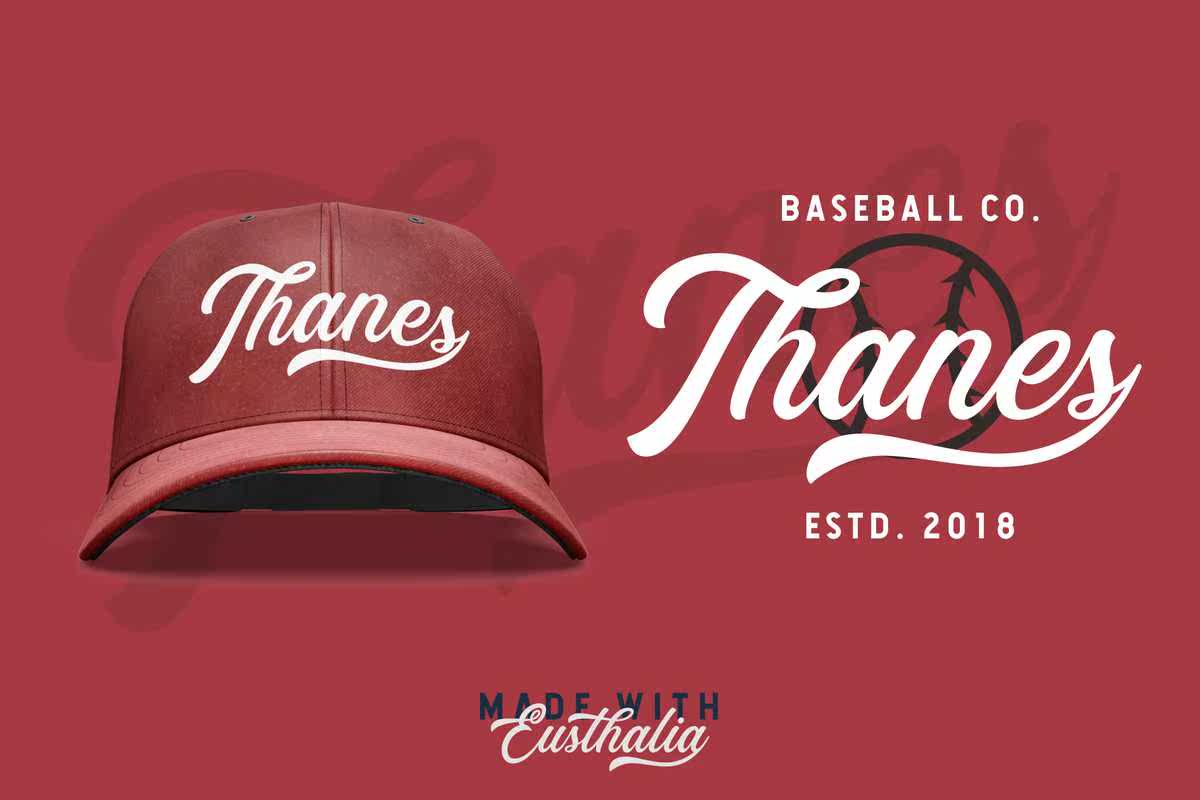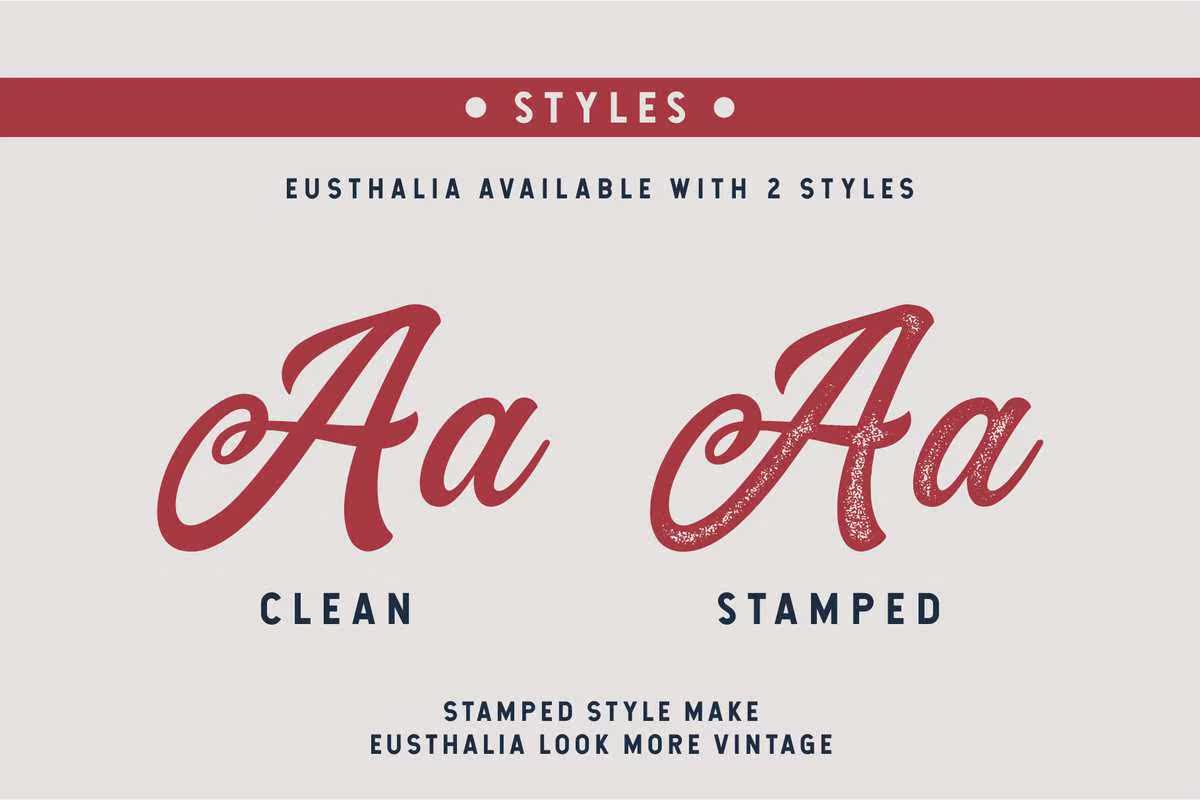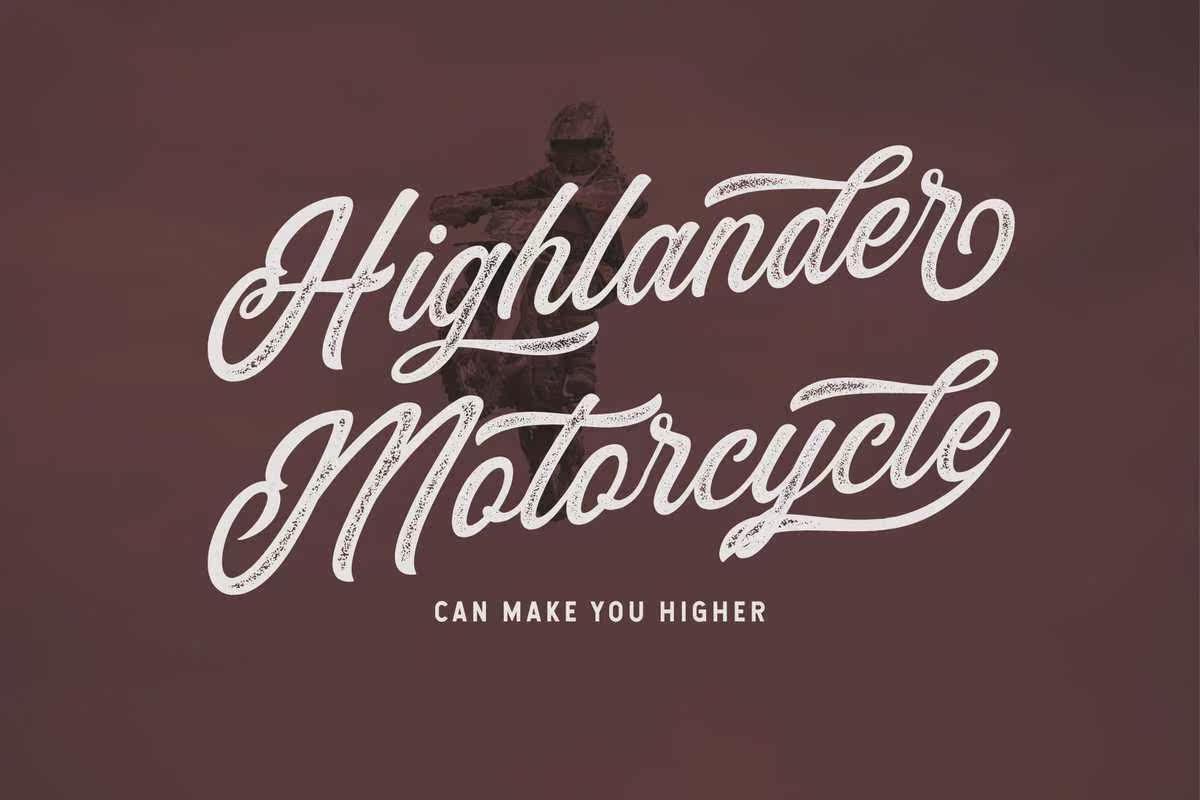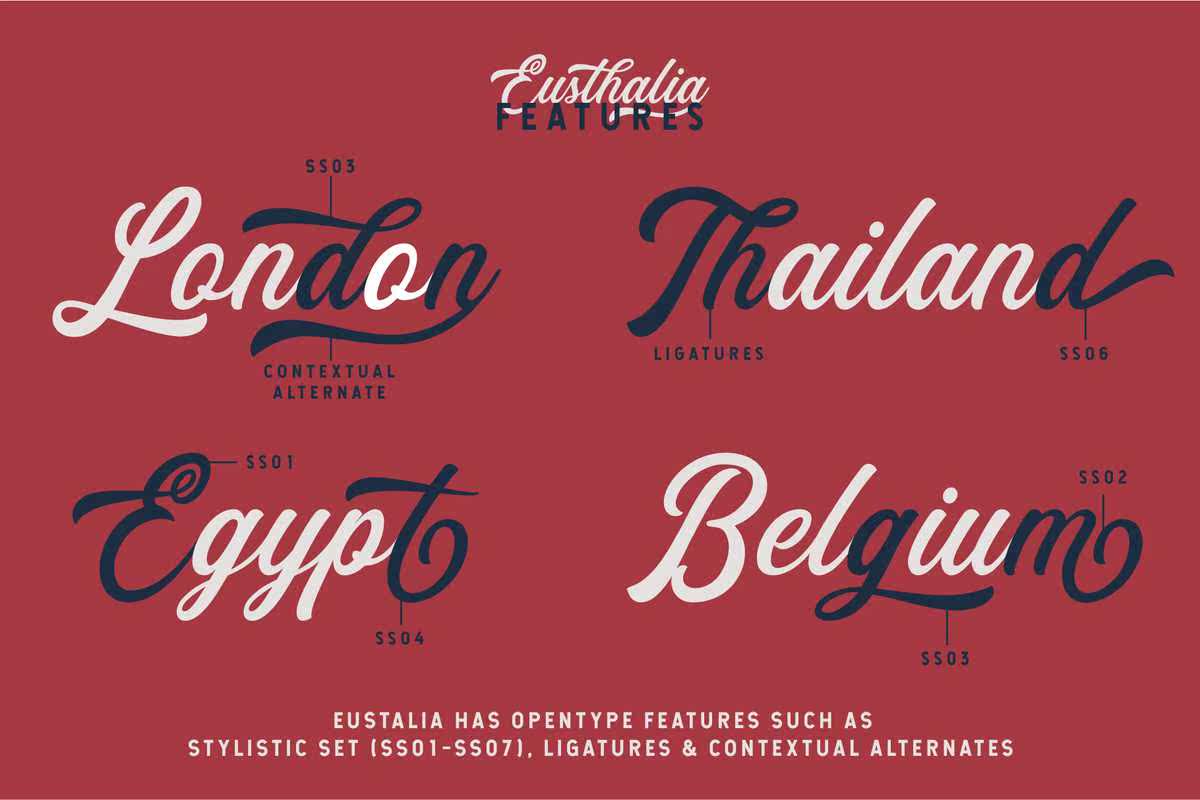
EusthaliatTypeface是一种ScriptFont,它有两种样式,一种是Clean,另一种是Stamped。有了这两种样式,EusthaliatTypeface可以用于印刷设计。EusthaliatTypeface还具有标准的多语言支持。(完整版)EusthaliatTypeface是一种ScriptFont,它有两种样式,一种是Clean,另一种是Stamped,EusthaliaTypeface可用于入侵设计。EusthaliaTypeface还具有标准的多语言支持。(完整版)